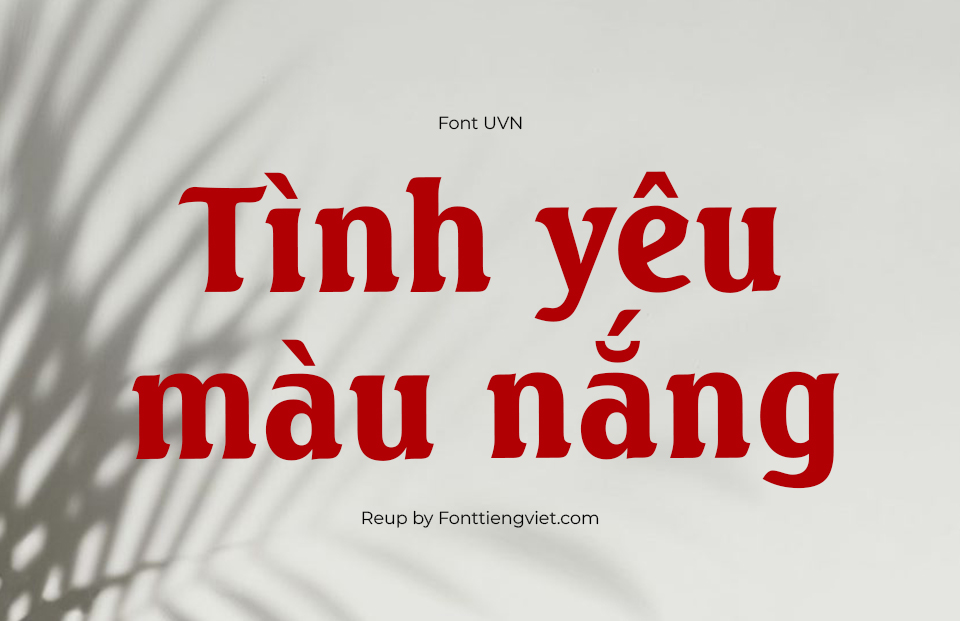
Trong thế giới thiết kế đồ họa học đường, việc lựa chọn một bộ Font Chữ phù hợp đóng vai trò quan trọng trong việc truyền tải thông điệp. Font Việt Hóa UVN Chim Bien Nang là một trong những lựa chọn hàng đầu dành cho các thầy cô và học sinh nhờ phong cách nét chữ chân phương, rõ ràng và đậm chất Việt. Bộ phông chữ này không chỉ giúp bài giảng trở nên sinh động mà còn đảm bảo tính thẩm mỹ cao cho các tài liệu in ấn văn phòng.
Đặc điểm nổi bật của Font Việt Hóa UVN Chim Bien Nang
Thiết kế tối ưu cho tiếng Việt
Bộ Font Việt Hóa UVN Chim Bien Nang được tinh chỉnh kỹ lưỡng để hiển thị hoàn hảo các dấu thanh trong tiếng Việt mà không bị lỗi font hay mất nét. Với độ đậm (bold) vừa phải, nó tạo ra sự tương phản tốt trên nền trắng, giúp người đọc dễ dàng theo dõi nội dung từ xa, đặc biệt là trên các bảng tin hoặc slide thuyết trình tại lớp học.
Ứng dụng đa dạng trong nhà trường
Nhờ vẻ ngoài thanh lịch và trang trọng, Font Việt Hóa UVN Chim Bien Nang thường được ưu tiên sử dụng để làm tiêu đề báo tường, thiết kế giấy khen hoặc các nhãn vở thủ công. Sự kết hợp giữa nét hiện đại và truyền thống giúp bộ chữ này mang lại cảm giác gần gũi nhưng vẫn chuyên nghiệp, phù hợp với mọi lứa tuổi từ mầm non đến trung học.